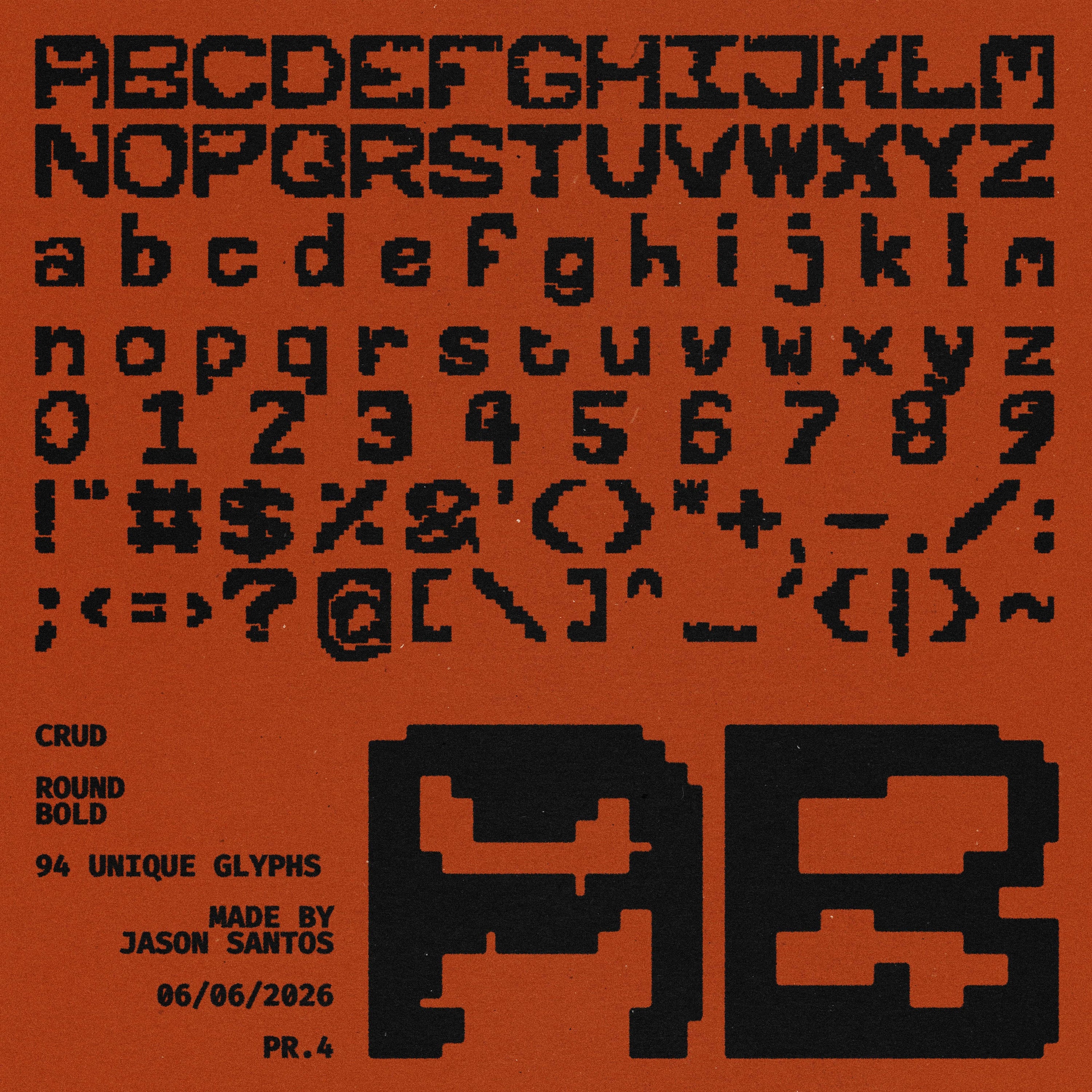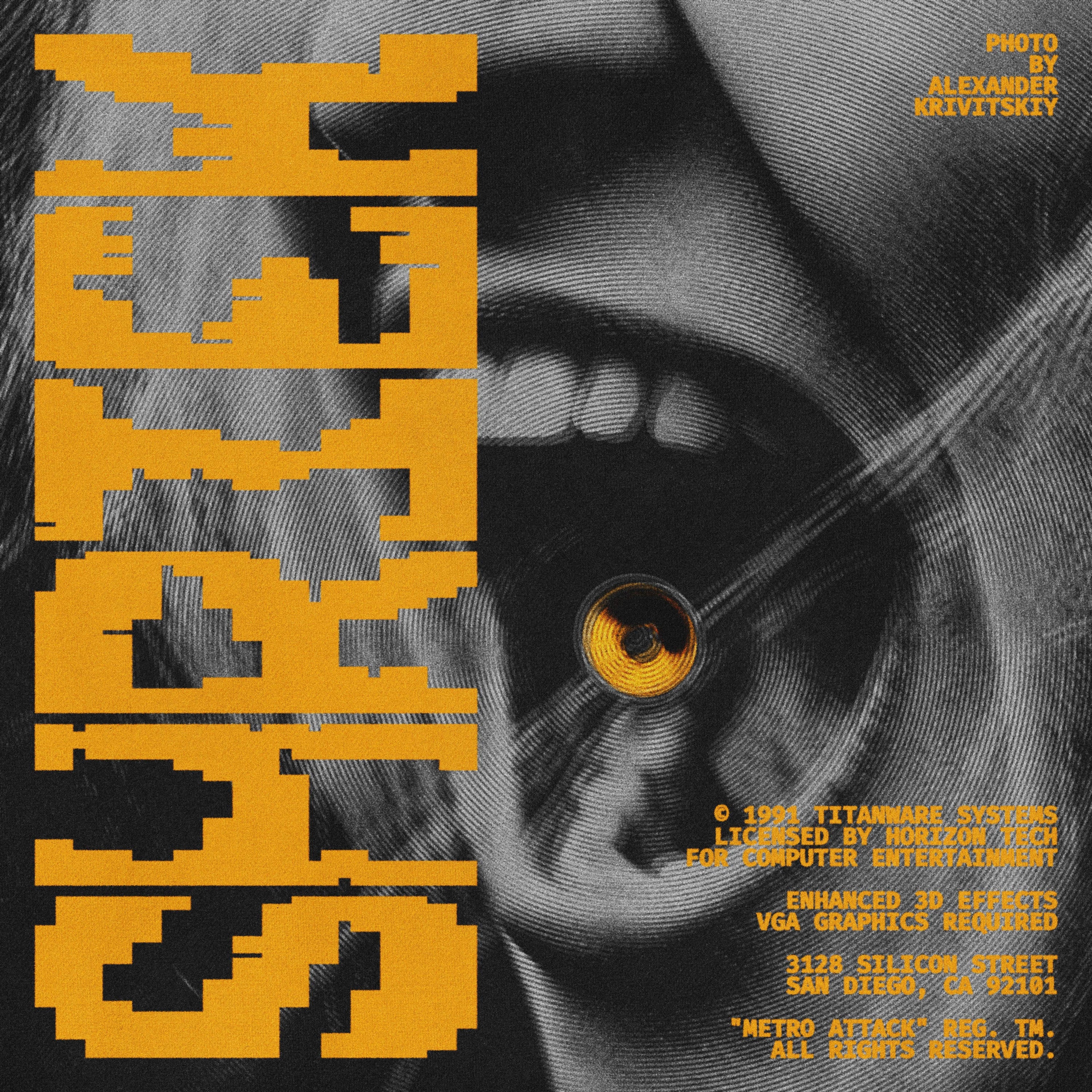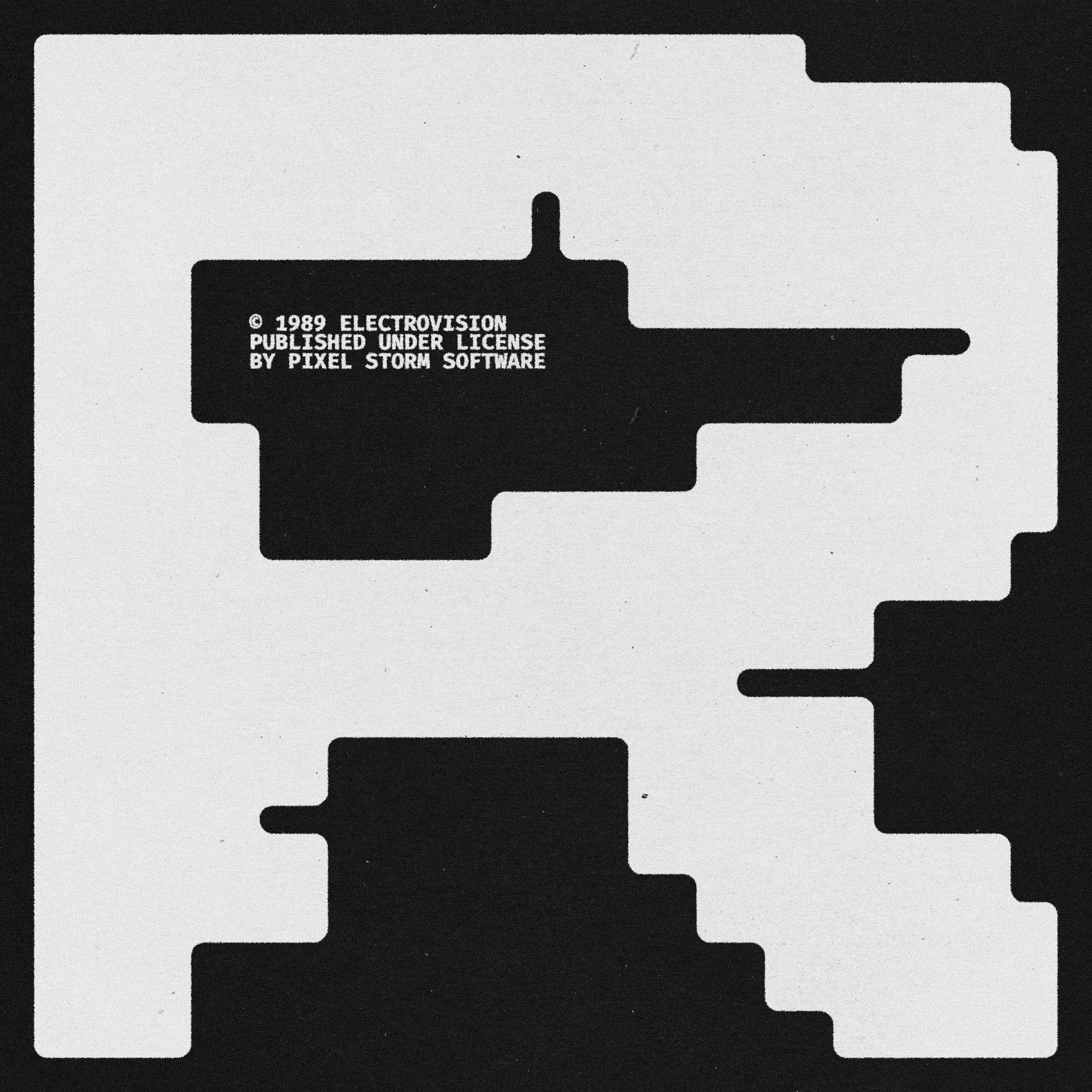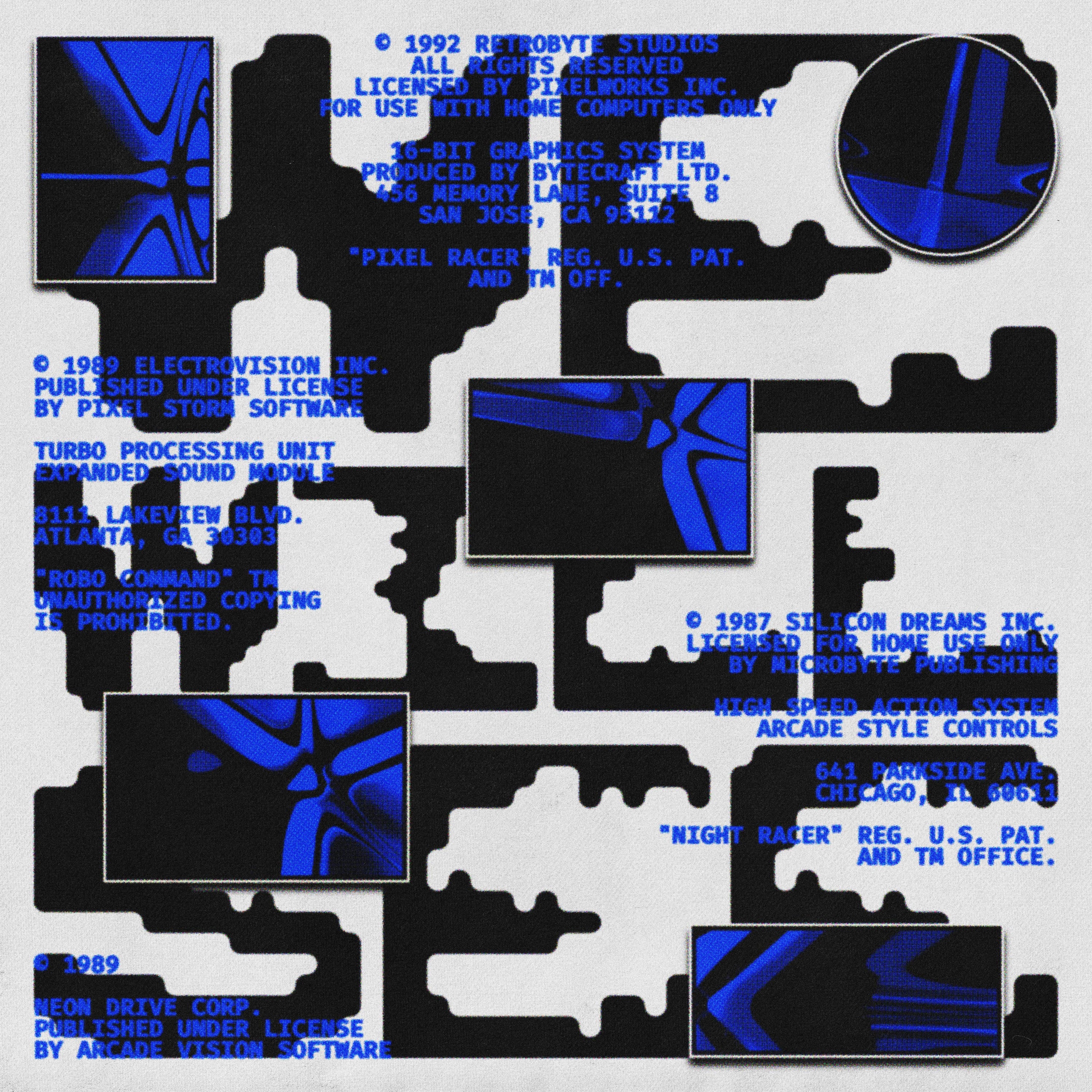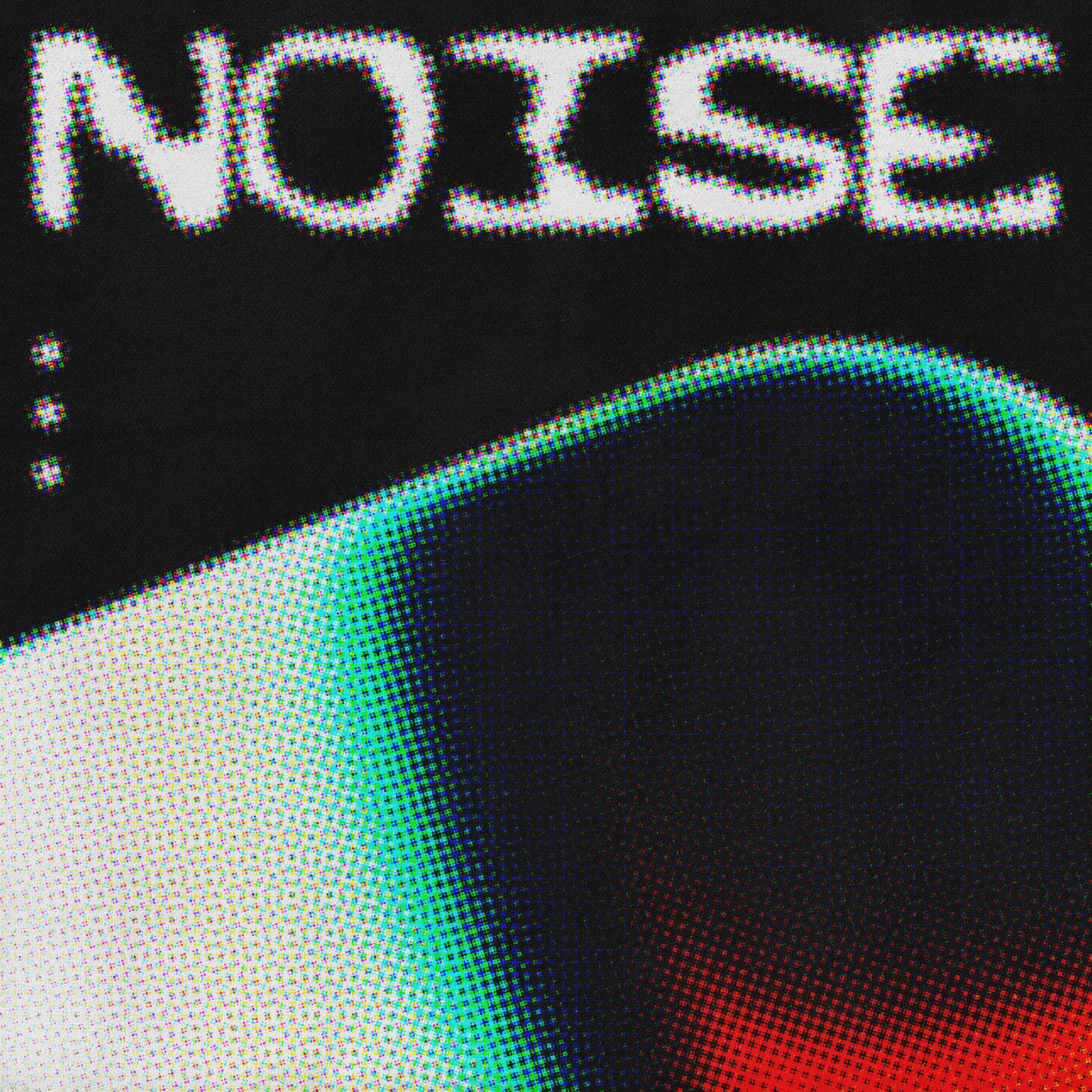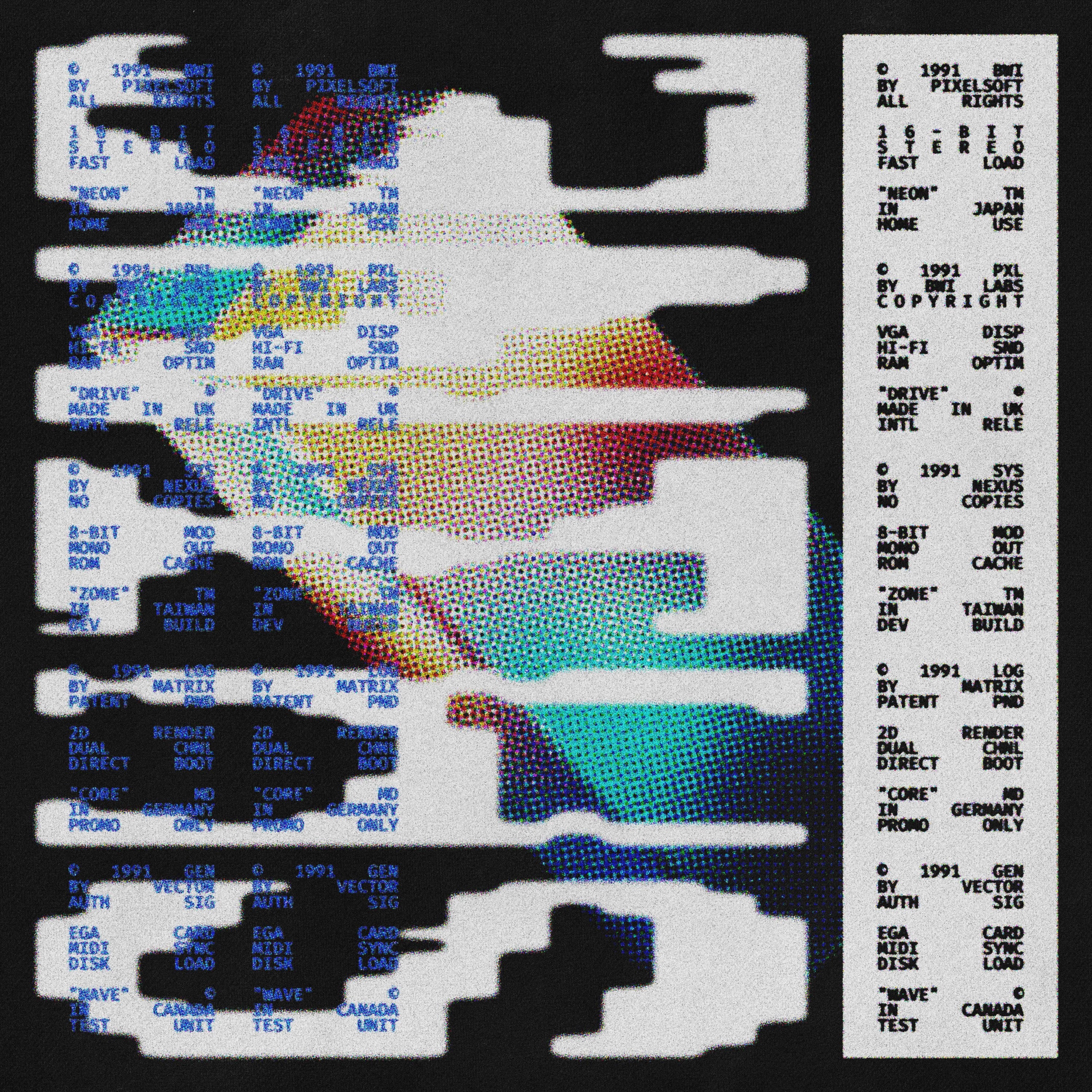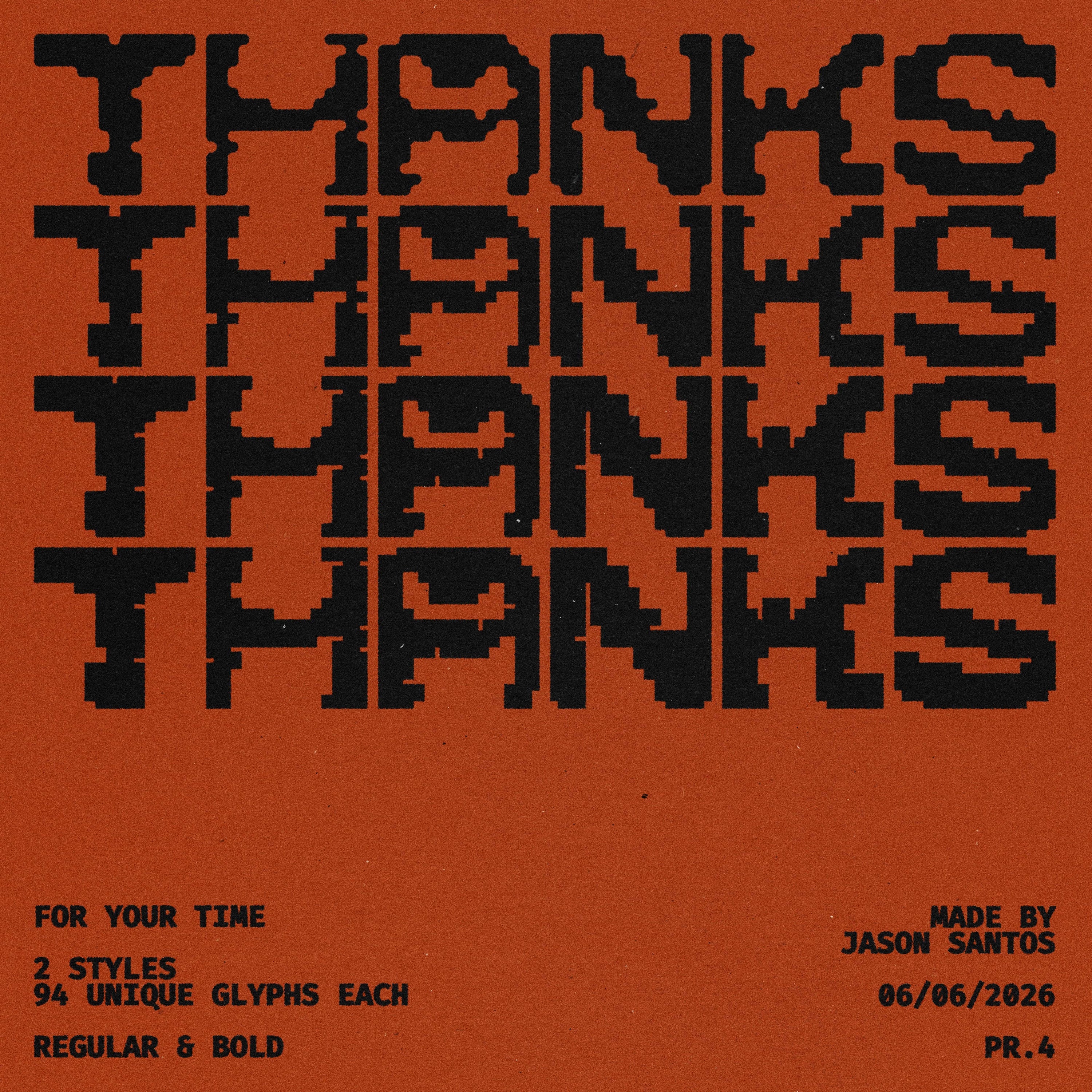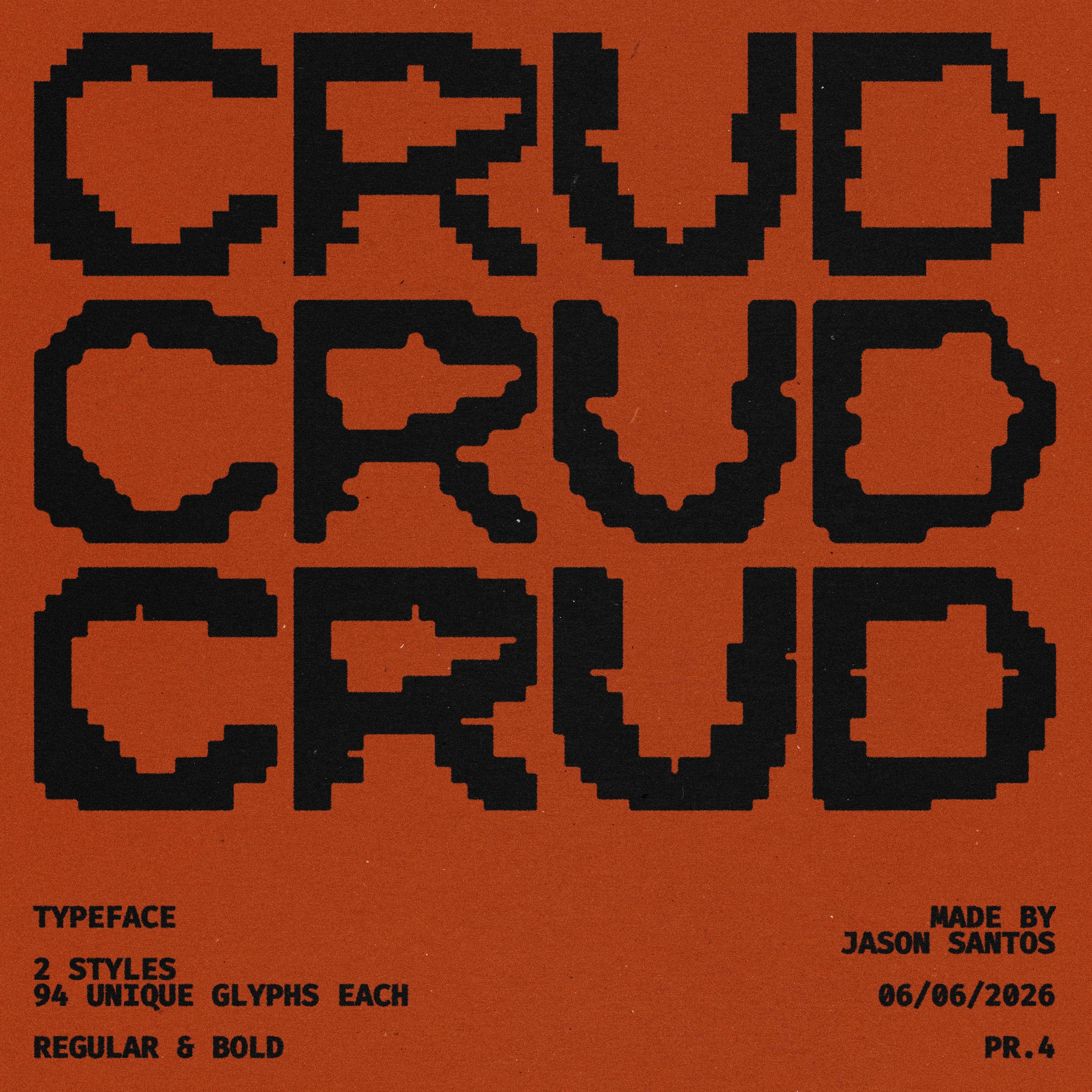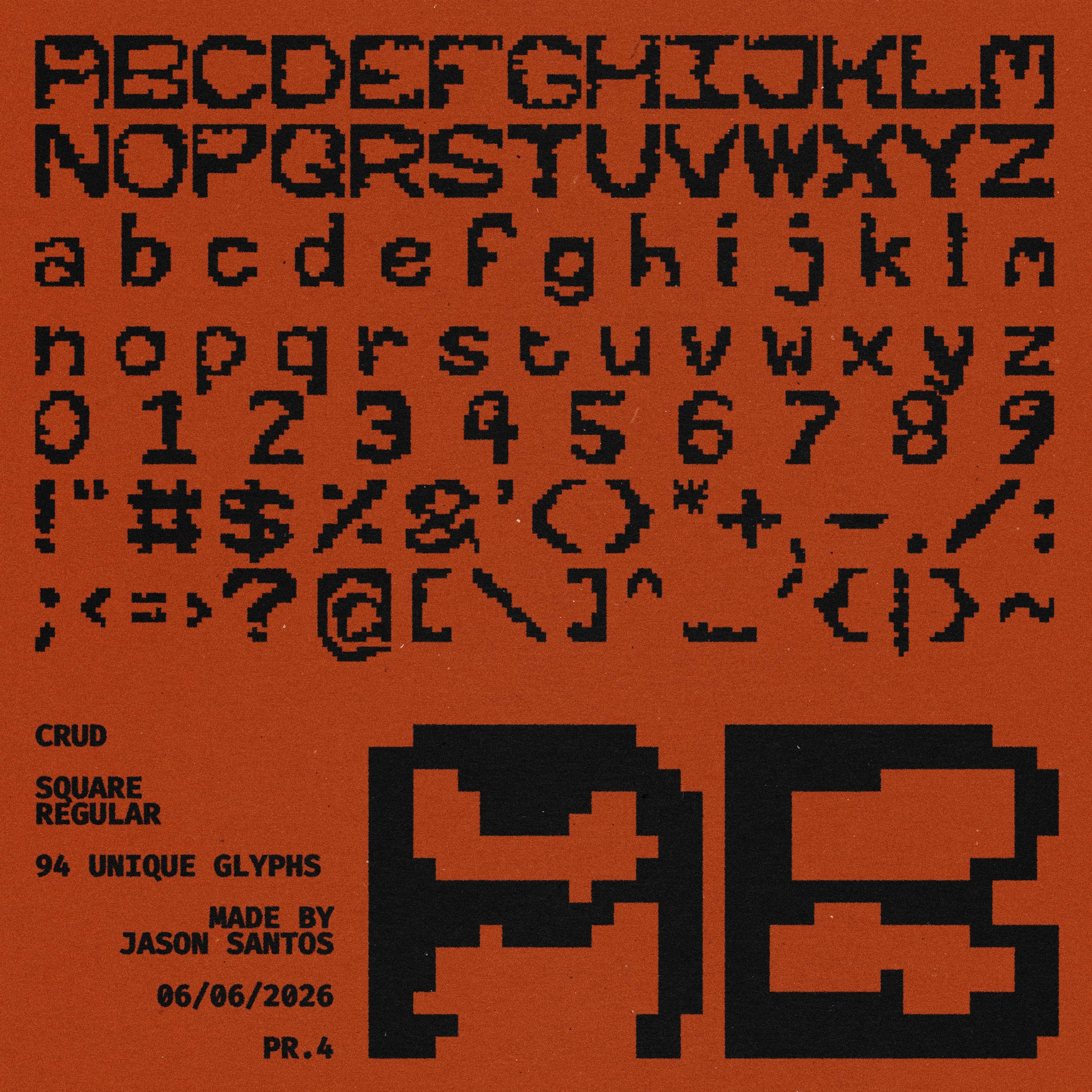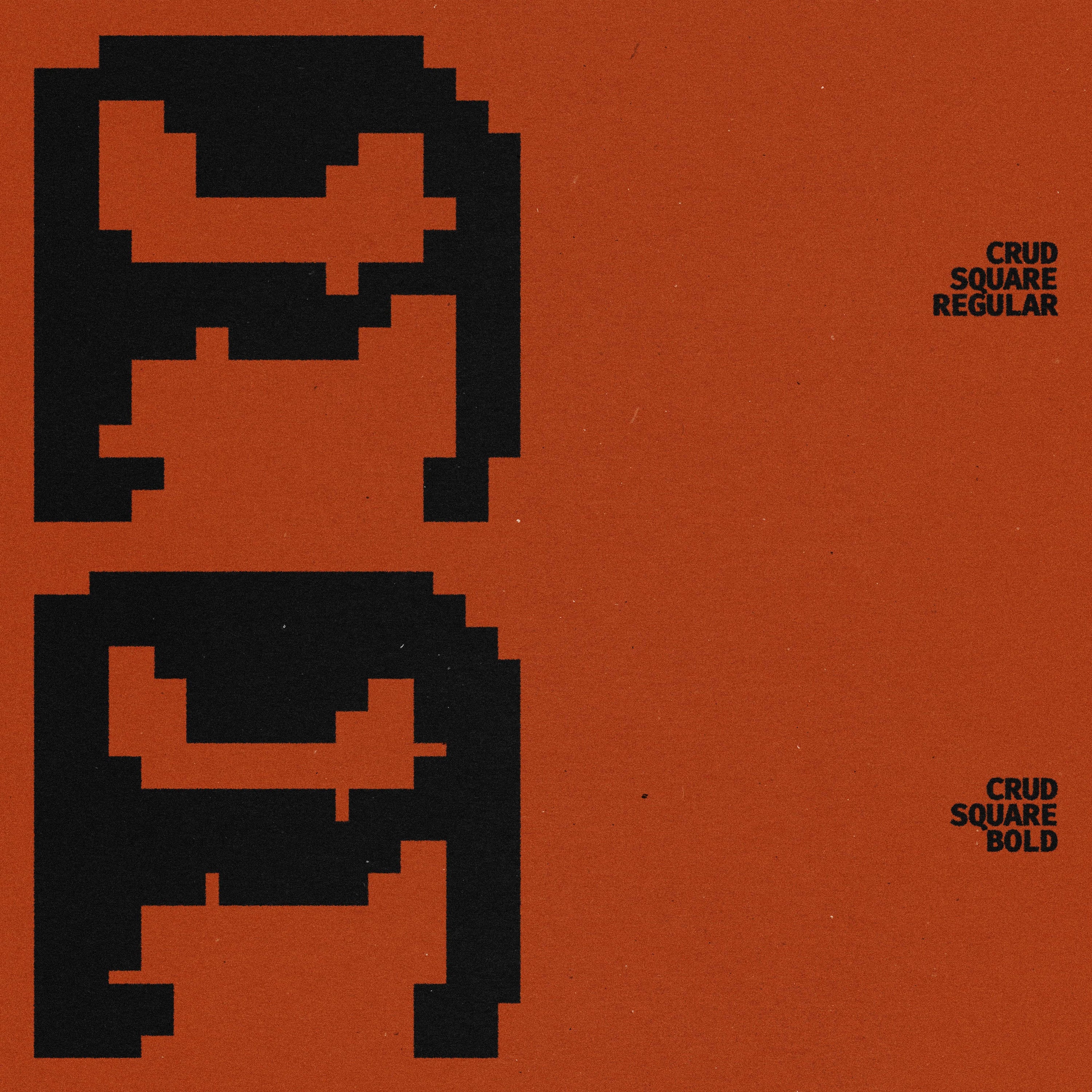
Tipografia Crud
Crud é uma fonte para títulos em pixels com inspiração retrô que captura o caráter imperfeito dos primeiros gráficos digitais. Com uma estética deliberadamente áspera e de baixa resolução, ela traz texturas nostálgicas de computadores e distorções digitais para a tipografia contemporânea.
Com duas variações — Square e Round —, Crud permite que designers explorem diferentes níveis de personalidade retrô, mantendo uma forte identidade pixelada. Suas formas marcantes funcionam especialmente bem em designs inspirados em jogos, tecnologia, estética cyber e cultura digital vintage.
Perfeita para pôsteres, logotipos, capas de álbuns, estampas para roupas, conceitos de interface, elementos visuais para jogos e identidade visual experimental.
Características
• 94 glifos
• 4 estilos (Square Regular, Square Bold, Round Regular, Round Bold)
• Letras minúsculas
• Letras maiúsculas
• Números
• Pontuação
• Símbolos
• Matemática